1. Rokurou Display Font
클래식과 모던함을 겸비한 독특한 스타일은 부드러운 외형과 우아한 럭셔리 함을 표현할 수 있는 서체입니다.
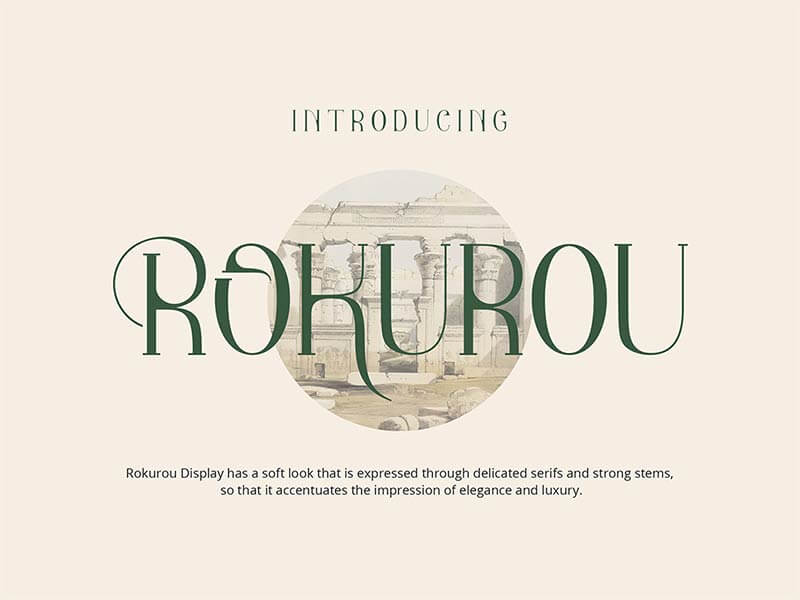
2. Allegra De Amour - Display
아름다운 곡선 형태로 복고풍 스타일의 산세리프 서체는 트렌드 중 하나입니다.
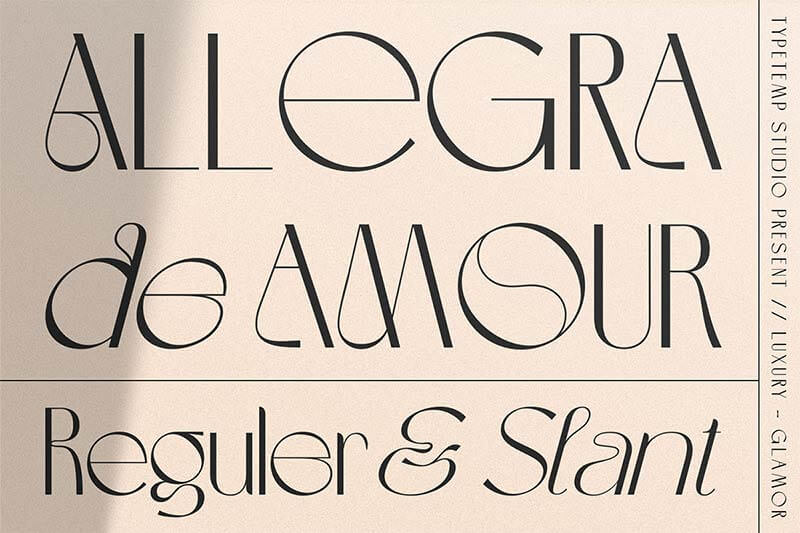
3. Roses Bolero - Free Elegant Sans Serif Font
최근 빈번하게 사용되는 고급스럽고 우아한 산세리프 서체계열의 폰트입니다.
로고 및 포스터 디자인, 잡지 등 폭넓게 이용할 수 있습니다.
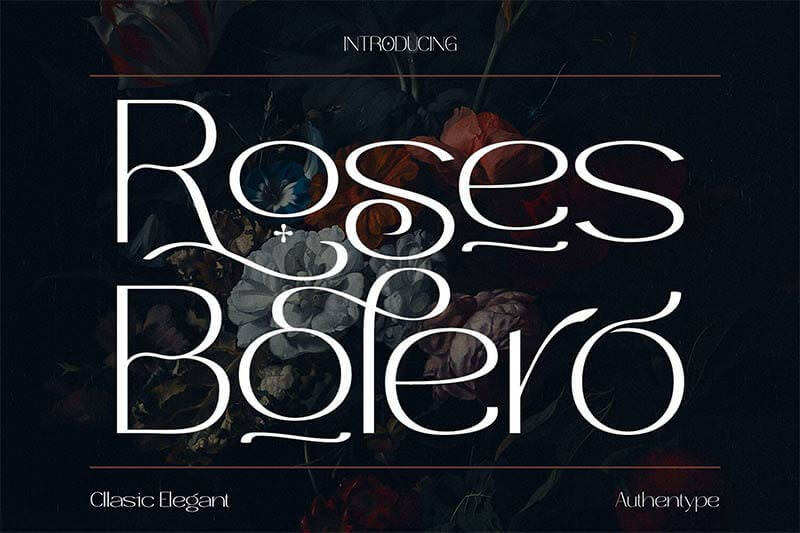
4. Hashira Mt - Free Luxury Serif Font
세련된 합자 및 대체 글꼴을 갖춘, 고급스러운 서체입니다.
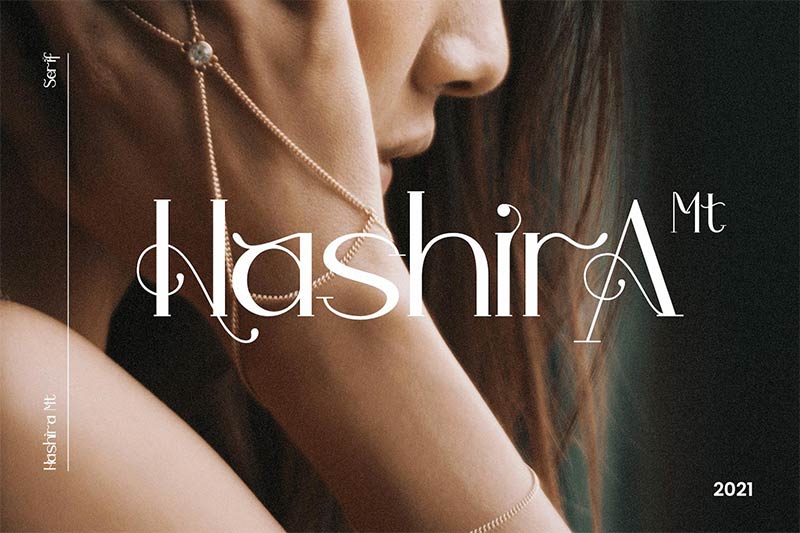
5. Grissed Vintage Typeface
오래된 빈티지 간판이나 포스터 등을 참고로 한 복고풍 글꼴로, 로고 디자인에 적합한 독특한 디자인이 특징입니다.
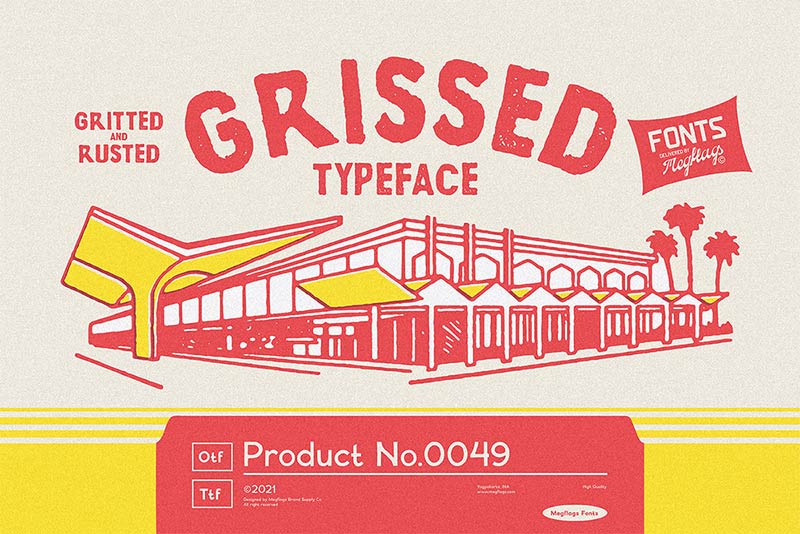
6. Daylosta Font
간단한 모노 라인으로 그려진 필기체 폰트는 클래식하고 우아한 스타일이 특징입니다. 유기농의 자연스러운 외형이 독특합니다.
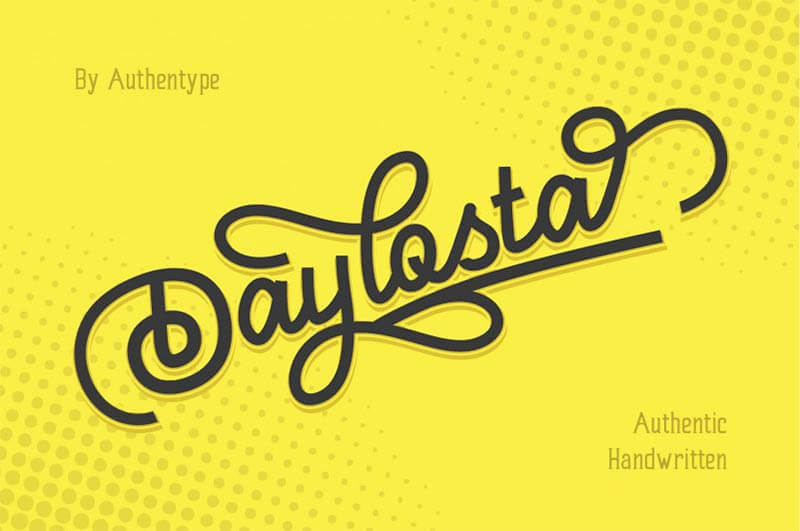
7. Saint Regus Font
자연스러운 왜곡을 글꼴에 추가한 굵은 산세리프 서체입니다.
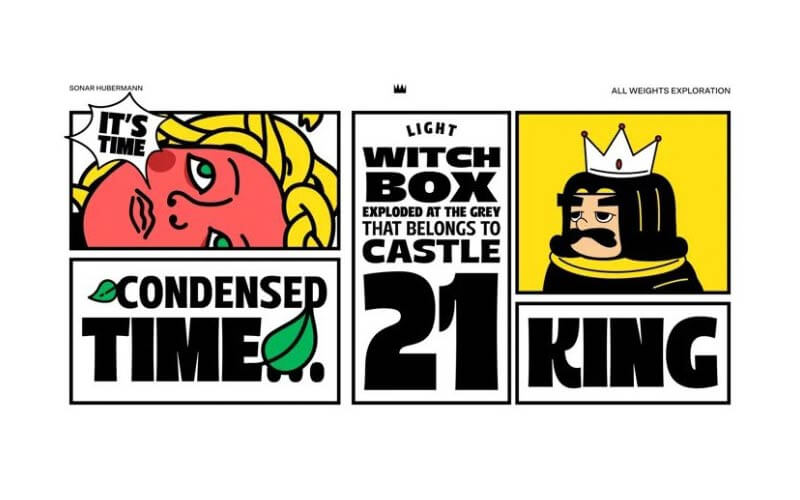
8. ENGINE Free Font
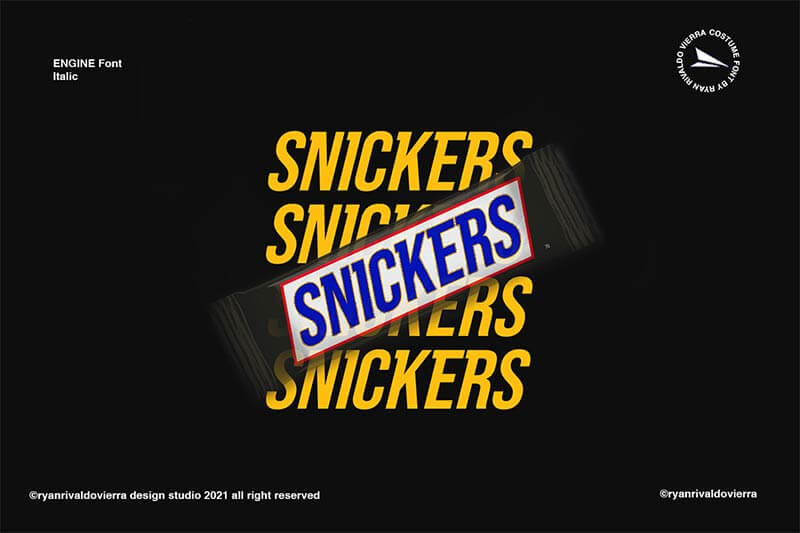
9. GarciaMarquez - Free TypeFace
콜롬비아 작가 가브리엘 가르시아 마르케스에게 애도의 뜻을 표한 추모 글꼴입니다.
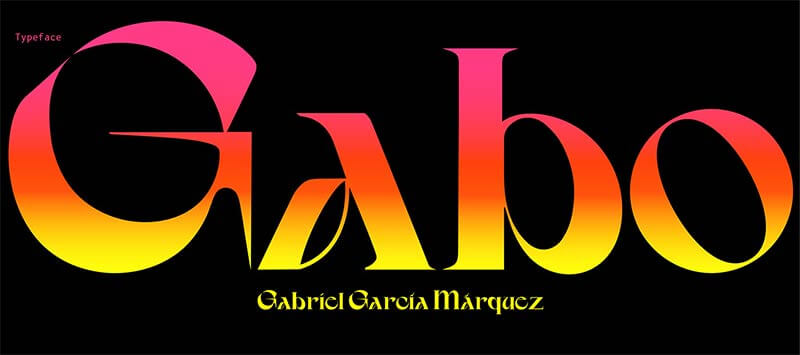
10. Hiatus - Free Brush Font
자연스러운 흐름이 돋보이는 브러시 질감을 재현 한 필기체입니다.
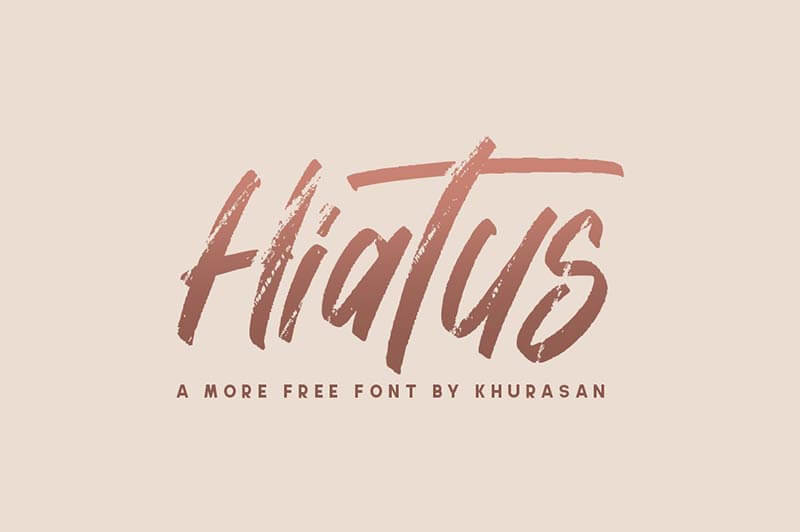
11. Summery Bold Handwriting Font
브러시로 필기 한 듯 거칠고 자연스러운 분위기의 무료 글꼴입니다.
12. Saturnalia Festive Script Font
팝으로 매력적인 로고를 만드는 데 최적화된 필기체입니다.
13. Sketchup
손으로 직접 스케치 한 것 같은 알파벳이 귀여운 무료 폰트입니다.
14. Britania Ligatura Display Serif
아름다움이 돋보이는 디스플레이 서체로 세련된 분위기를 연출하고 싶을 때 활용하기 좋은 서체입니다.
15. Fragille Modern Typeface
모던하고 세련된, 고급스러운 서체입니다.
초서체와 필기 글꼴이 함께 어우러진 분위기가 멋집니다.
16. Free Morthsside Calligraphy Font
생동감 넘치는 아름다운 필기체 폰트로 붓 브러쉬의 필체를 그대로 필기 스타일이 특징입니다.
17. Stone Board - Free Vintage Display Font
아름다운 빈티지 사인에 그런지 느낌을 더한 복고풍 글꼴의 하나입니다.
대체 글꼴도 일부 포함되어 있어 디자인에 편리한 느낌입니다.
18. Wata Free Sans Serif Font
굵은 선과가는 곡선을 조합 한 인상적인 디스플레이 서체입니다.
가독성은 좋지 않지만, 포스터 등의 제목을 강조하고 싶을 때 사용하면 좋습니다.
19. KUBAN PRO Typeface - (Free Font)
글꼴의 중심을 약간 아래로 내려 독특한 오리지널과 레트로 스타일을 양립 한 서체입니다. 키워드 등 짧은 단어에 최적입니다.
20. Salma - Free Sans Serif Font
현대적이고 우아한 산세리프 서체로, 무료 데모로 Light와 Light Italic 2 글꼴이 제공되고 있습니다.